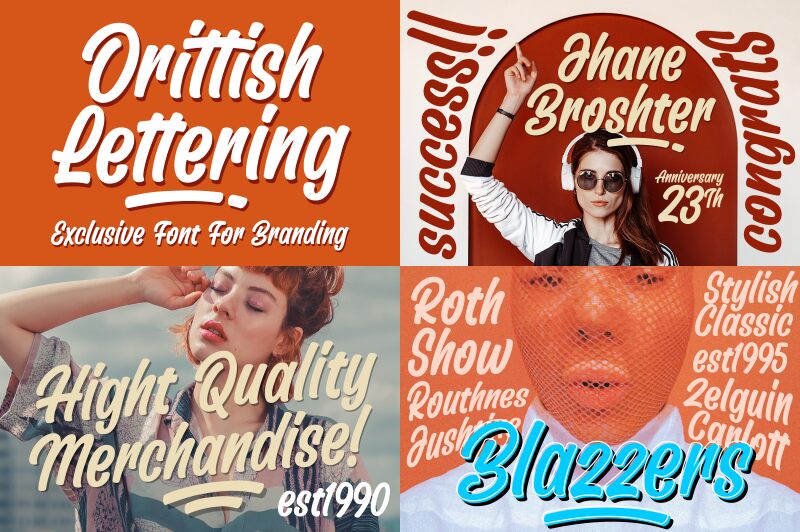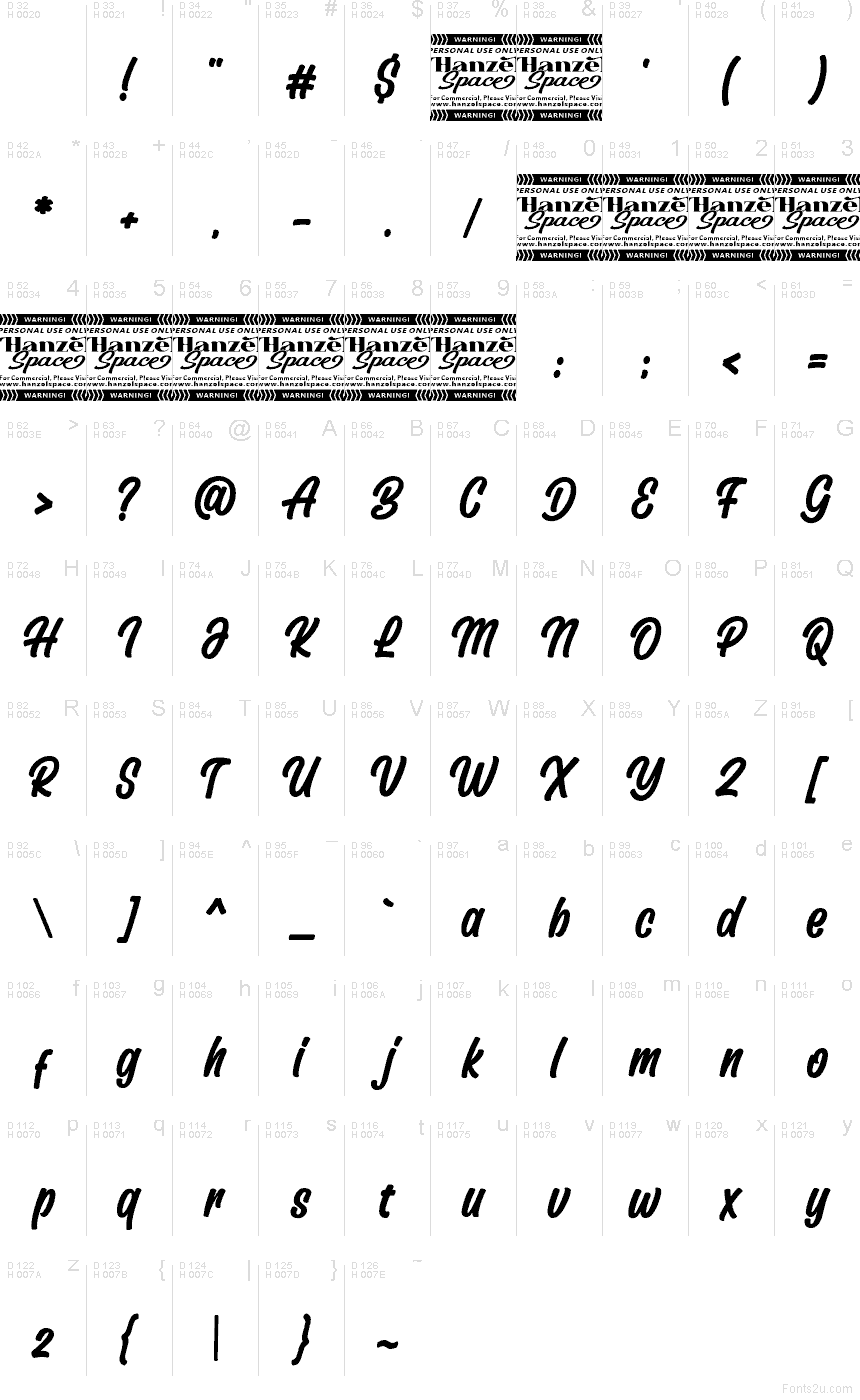
Orittish, da Hanzel Space, é uma fonte gratuita de estilo pincel com um balanço rápido e pintado à mão. As letras apostam em traços espessos e arredondados com conexões suaves, além de uma abertura em laço e barras transversais compactas em letras duplas, conferindo à fonte um ar casual, ousado e levemente retrô, sem ser rebuscada.
Combina perfeitamente com títulos de cartazes, branding de cafeterias, etiquetas de produtos, artes para redes sociais e chamadas curtas em embalagens onde uma fonte gratuita precisa transmitir calor em vez de um acabamento polido. Use-a para nomes, capas ou logotipos curtos: o ritmo de pincelada robusta e o espaçamento justo dão às palavras, mesmo as curtas, um impulso manuscrito cheio de vida.
Orittish inclui caracteres maiúsculos e minúsculos, pontuação e números. Suporta idiomas internacionais e inclui recursos OpenType com variantes estilísticas.
Os caracteres desta fonte não são conectados uns aos outros.
Variantes estilísticas para caracteres minúsculos chave estão disponíveis e podem ser acessadas no painel de Glifos do Adobe Illustrator ou em Alternativas Estilísticas no menu OpenType do Adobe Photoshop.
- Conjunto completo do alfabeto padrão e pontuação
- Conjunto extra de minúsculas com traços finais
- Ligaduras manuscritas
- Caracteres multilíngues (ẂŴẄẀŶỲ ẃŵẅẁŷỳ)